Tutorial tipografía: 3 consejos para escoger una tipografía
Tips prácticos para elegir una tipografía, a tener en cuenta antes de iniciar tu proyecto de diseño gráfico
Cuando queremos comunicar algo, tan importante es decidir lo que decimos como la forma de decirlo: tan importante es el contenido como la forma. A la hora de iniciar un proyecto de diseño gráfico en el que vayamos a incluir textos, esta norma es si cabe más esencial todavía: la tipografía que elijamos (la forma) transformará completamente lo que queremos decir (el contenido).
Para ayudarte a la hora de escoger una tipografía para tu proyecto, el diseñador gráfico especializado en diseño editorial Enric Jardí (@enricjardi) tiene 3 consejos esenciales que siempre hay que tener en cuenta.
1. Tipografías de lectura y tipografías de display
Muy probablemente, en nuestro proyecto existirán textos de tamaños diversos: títulos, subtítulos, párrafos enteros de texto más pequeño... conocer la diferencia entre las tipografías de lectura y de display nos ayudará a escoger el tipo de letra para cada uno de los tamaños.
Tipografías de lectura
Aunque obviamente todas las letras son para leer, llamamos de lectura a aquellas que surgieron para su uso en libros en tamaño pequeño, como la romana y los distintos tipos que se derivaron de ella (redonda, cursiva, versalitas y más grande para portadas y otros títulos).
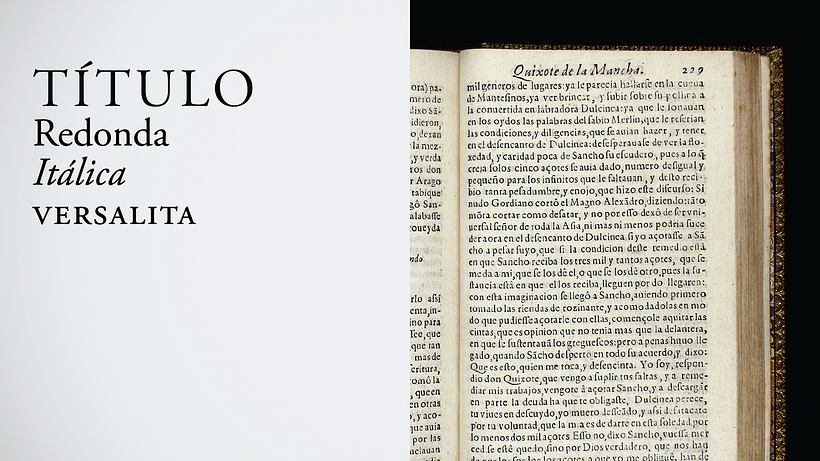
Tipografías display
Con el auge de la cartelería, las letras "salen a la calle" y se impone la necesidad de crear tipografías que se vean desde lejos. Así es como se desarrollan las tipografías display, entre ellas las de palo, las egipcias o las ornamentadas, letras construidas ya no con materiales como el metal sino con otros más maleables como la madera.
Las display están más indicadas para carteles, textos breves o necesidades similares, y no se recomienda utilizarlas para el texto normal de un libro.
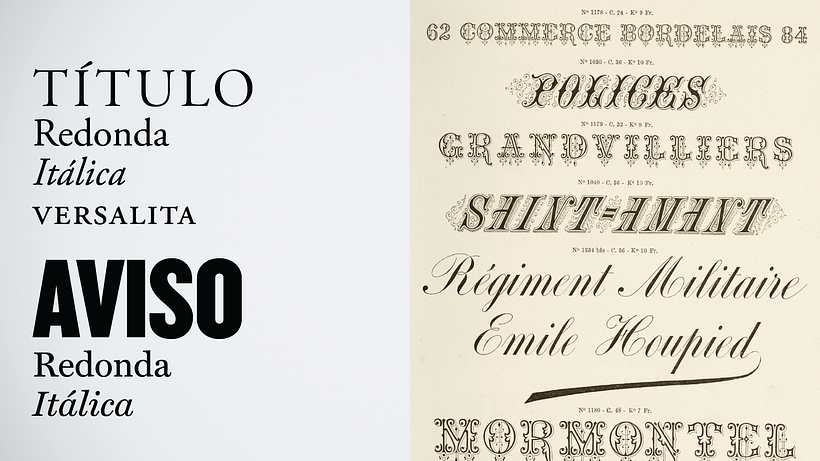
2. Tipografías de papel y tipografías de pantalla
Cuando nos pongamos a diseñar en nuestra computadora, habrá dos tipos de letra que podremos utilizar: las creadas expresamente para su uso digital y las que ya existían antes y que se "importaron" para uso en computadoras.
Tipografías de papel
Ya sean de lectura o de display, las tipografías de papel se crearon antes de la aparición del diseño digital. Son letras como la Times New Roman, Palatino, Courier, Impact o Arial. Aunque obviamente han sido adaptadas para computadora y su uso está muy extendido en el mundo digital, se considera que se ven mejor impresas que en una pantalla.
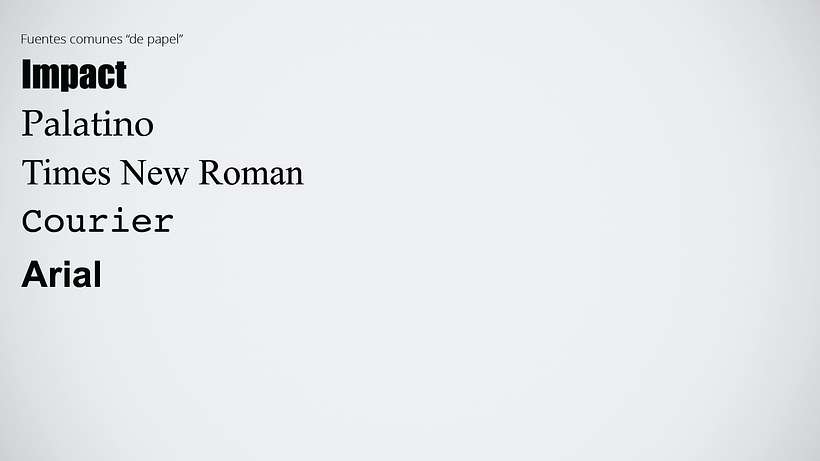
Tipografías de pantalla
Son tipos de letra que se diseñaron especialmente para computadora y que se considera que se ven igual de bien tanto en papel como en pantalla: Georgia, Verdana, Tahoma, Trebuchet...
Por lo tanto, si por ejemplo estamos diseñando una web, lo ideal será utilizar las tipografías de pantalla para los cuerpos pequeños (ya que están mejor optimizadas para computadora) y las tipografías de papel para los títulos, subtítulos u otros textos destacados.
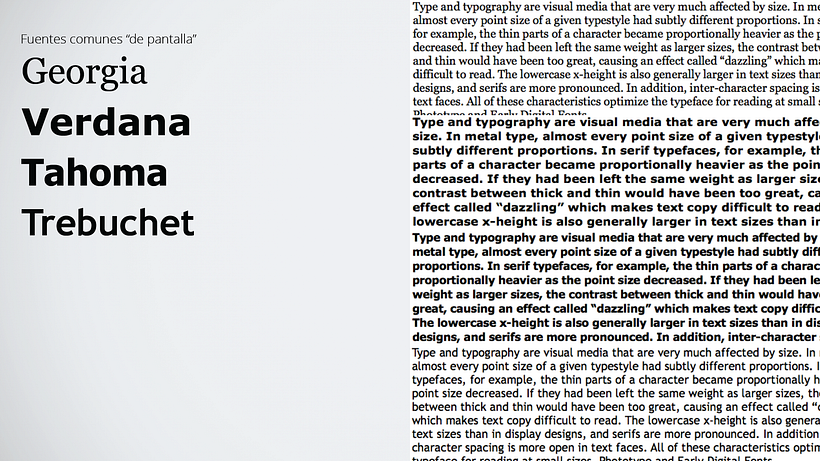
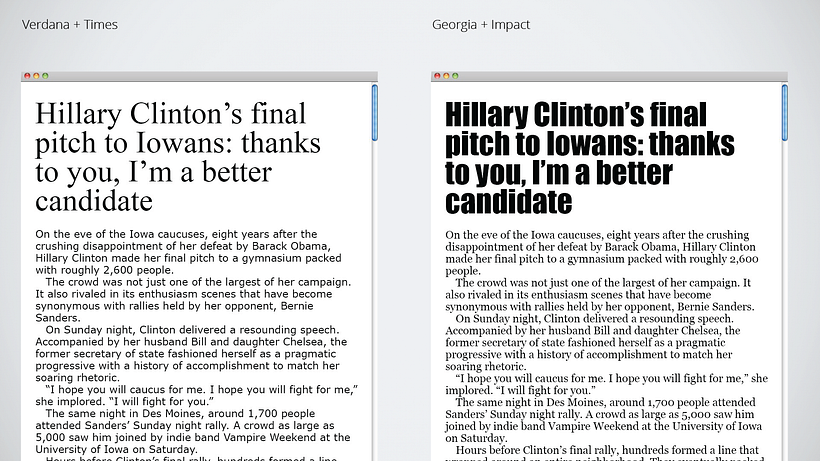
3. Cada tipografía cuenta una cosa distinta
Es la regla básica del diseñador editorial: debemos escoger la letra que se adecúe exactamente a lo que queremos contar. Porque cada tipografía tiene su estilo, y cada uno de ellos nos cuenta cosas completamente distintas.
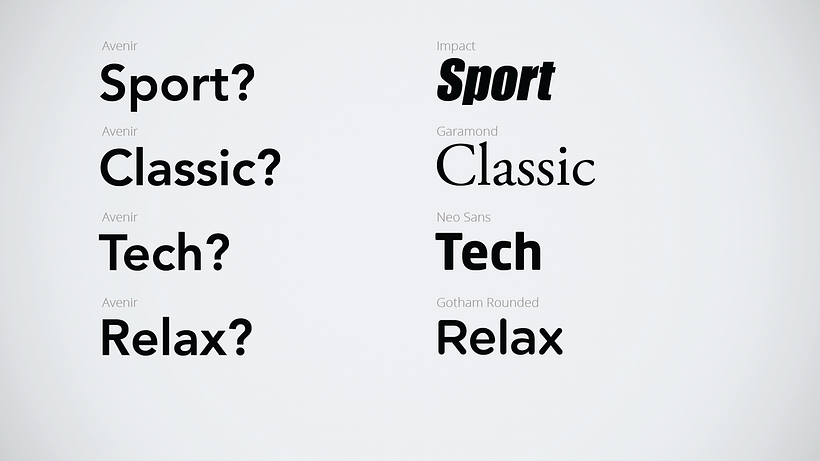
Pero, más allá de tener en cuenta para qué funciona cada tipografía, es importante considerar para qué no funciona. Como veremos en las siguientes fotografías, una letra gótica puede funcionarnos tanto para un grupo de rock como para algún libro sobre el Medievo, pero quedará muy extraño si, por ejemplo, la utilizamos en la tarjeta de visita de un dentista: